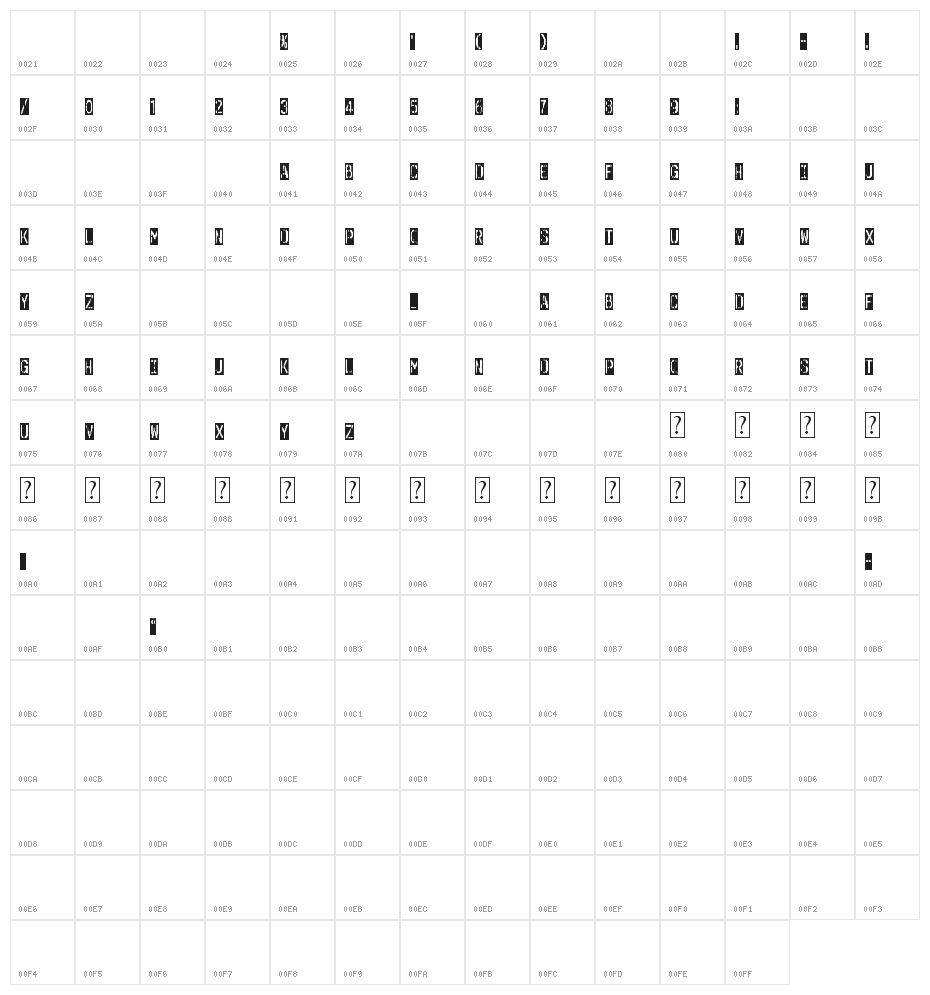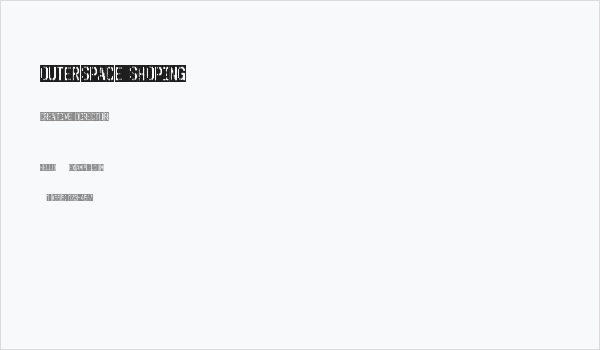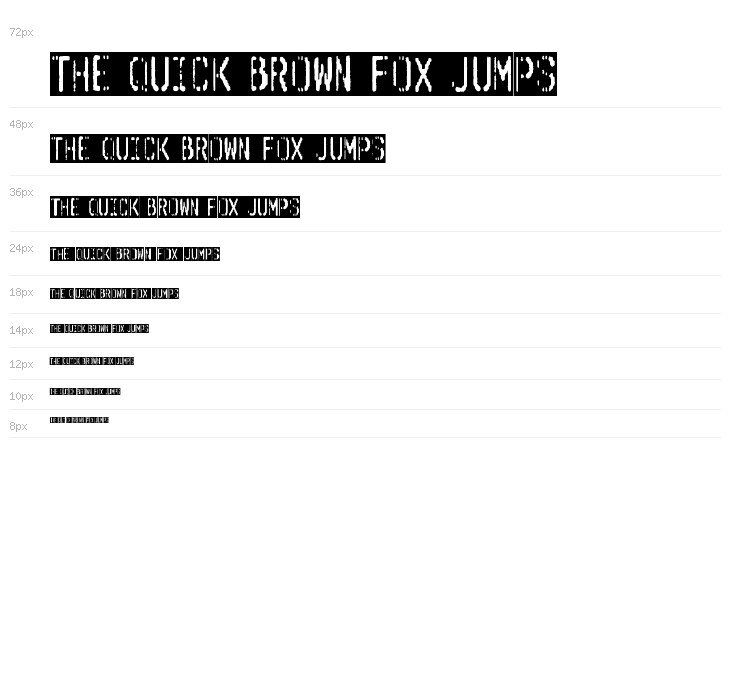
Outerspace Shoping Font
✎ Stencil
| カテゴリ | Stencil |
| 全体的なスタイル | Grunge, Industrial |
| おすすめプロジェクト | Ideal for posters, album covers, urban-themed branding, and edgy graphic designs. |